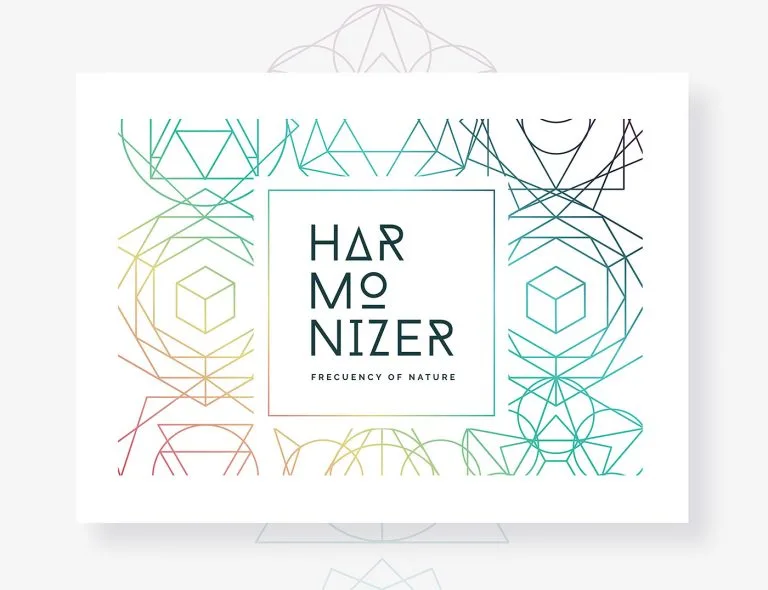
Designer cria série fantástica de tipografias criativas
A colombiana Ana Mondragon é uma talentosa designer especializada em branding, impressão e embalagem.
Ela é apaixonada pelo conceito que existe por trás de cada criação, e dedica todo o seu tempo para transformar as suas criações em algo único e inovador.
Suas tipografias são modernas, fantásticas, cheias de detalhes, e isso ficou bem claro em uma série criativa de tipografias que ela compartilhou recentemente.